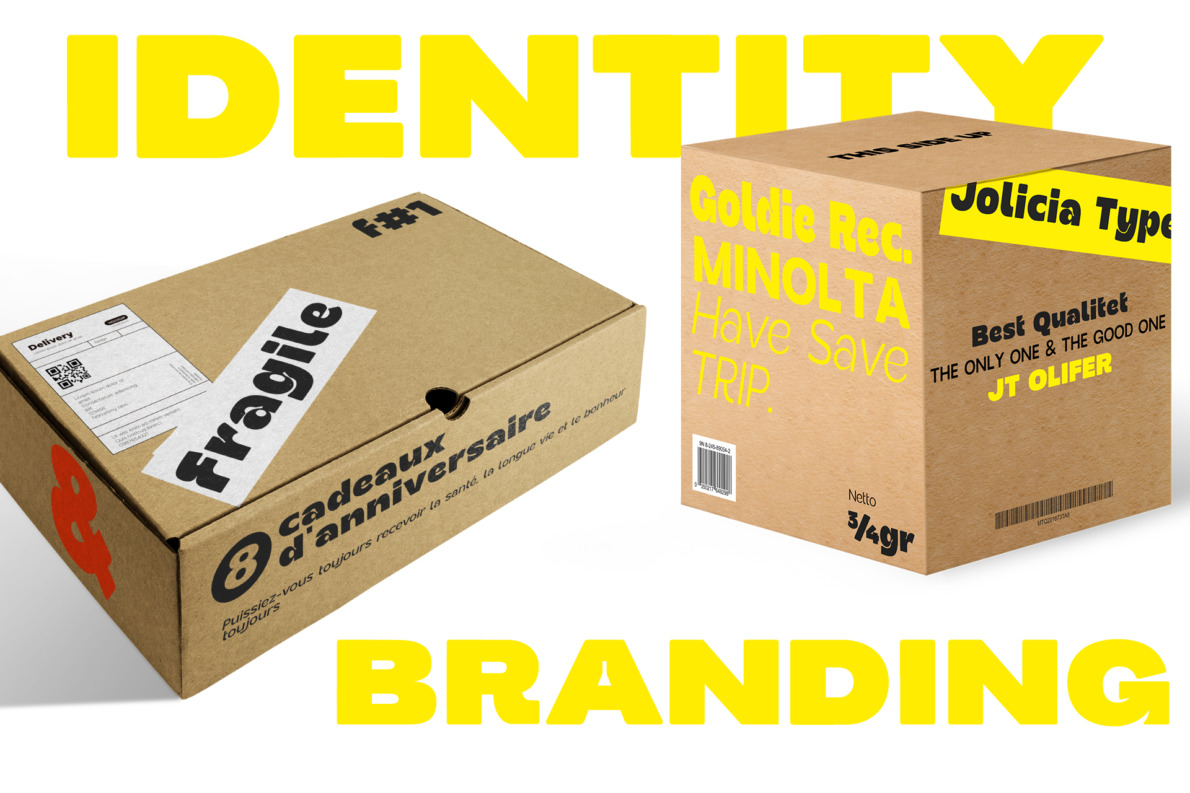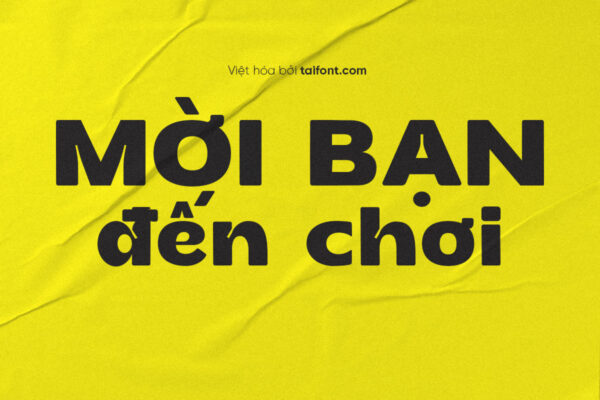
Font Việt hóa TF JT Olifer SemiBold là một font không chân hiện đại, rất thích hợp cho các thiết kế ẩm thực.
Với kiểu chữ sắc nét và phong cách thanh lịch, nó tạo ấn tượng mạnh mẽ và dễ đọc. JT Olifer là lựa chọn tuyệt vời cho font tiêu đề, giúp thu hút sự chú ý và làm nổi bật thông điệp trong các dự án của bạn.
Font Việt hóa TF JT Olifer SemiBold – Font ẩm thực nét tròn